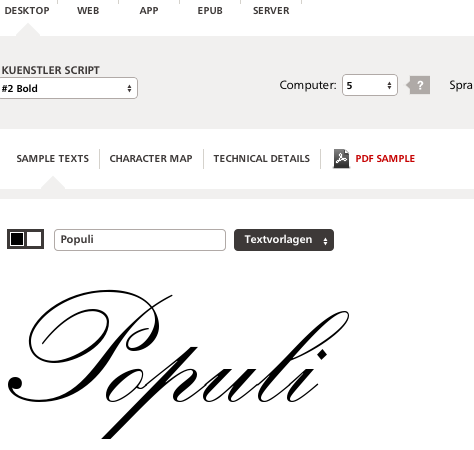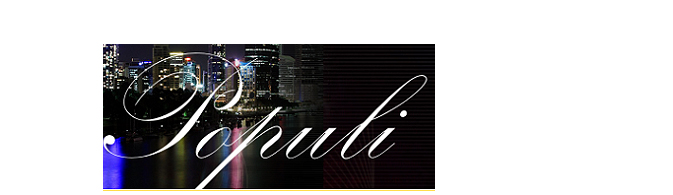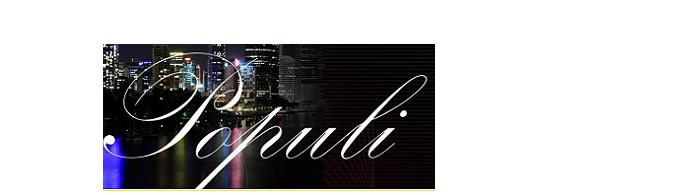
Suche kursive Schrift des Restaurantsnamen "Populi"
Wer kann mir sagen, in was für einer Schrift dieser Restaurantname geschrieben ist.
… beispielsweise bei linotype – bis auf den i-punkt. der ist in deinem beispiel rund.